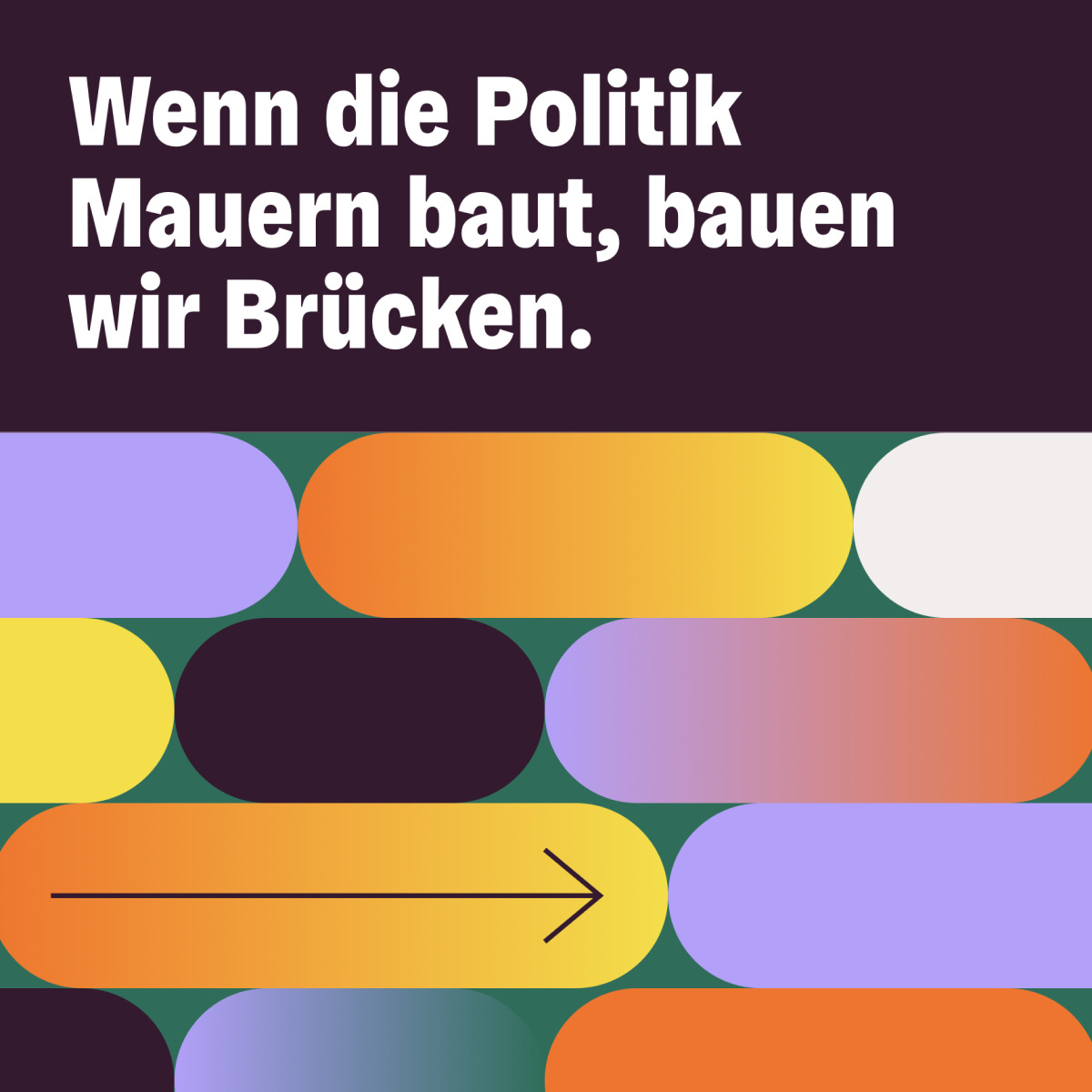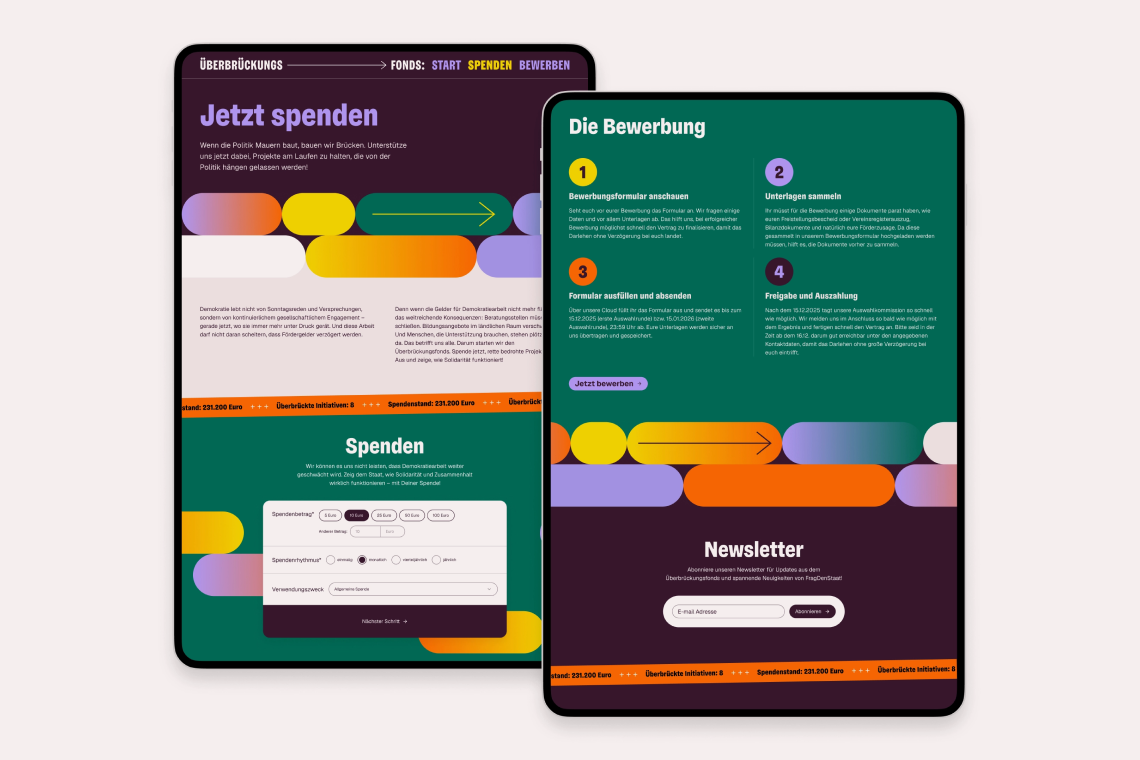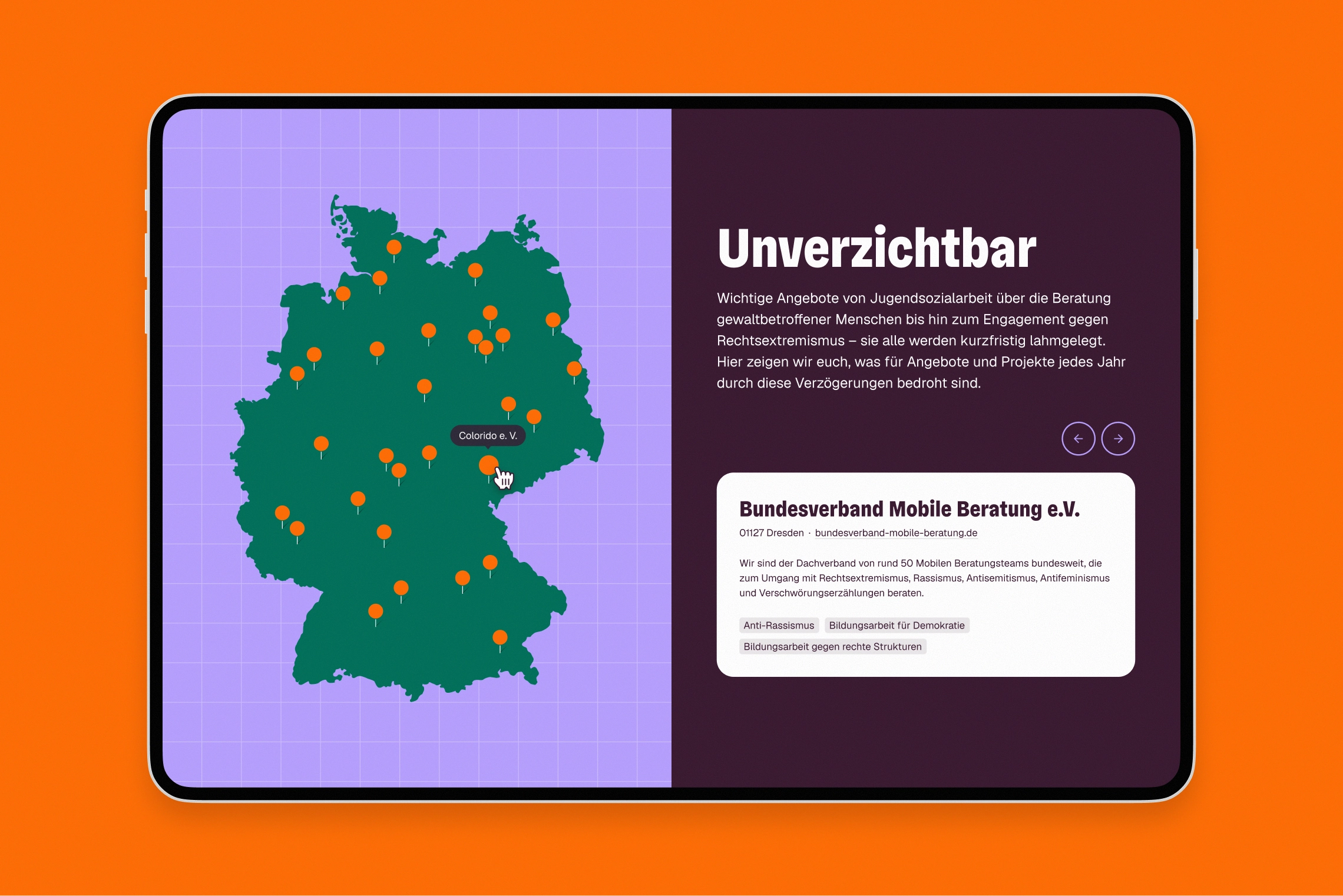
Gregory Grotesk в работе: Überbrückungsfonds
Инициатива, которая помогает тем, кто ждёт помощи, и искренний интерфейсный гротеск
Überbrückungsfonds — фонд, который помогает небольшим независимым немецким проектам избежать кассовых разрывов, которые часто случаются потому, что государственные дотации малому бизнесу задерживаются. На сайте проекта, оформленном Кристофом Раушером, за типографику отвечают Gregory Grotesk Compressed студии TypeMates и Inter Расмуса Андерсона.
Gregory — коллекция из четырёх шрифтов — одной антиквы и трёх гротесков. Антиква — Gregory Poster — вдохновлена леттерингом с обложек винтажных книг, а гротески — Gregory Grotesk, Gregory Grotesk Condensed и Gregory Grotesk Compressed — стремятся добавить в стерильную цифровую среду каплю аутентичности ручного набора.